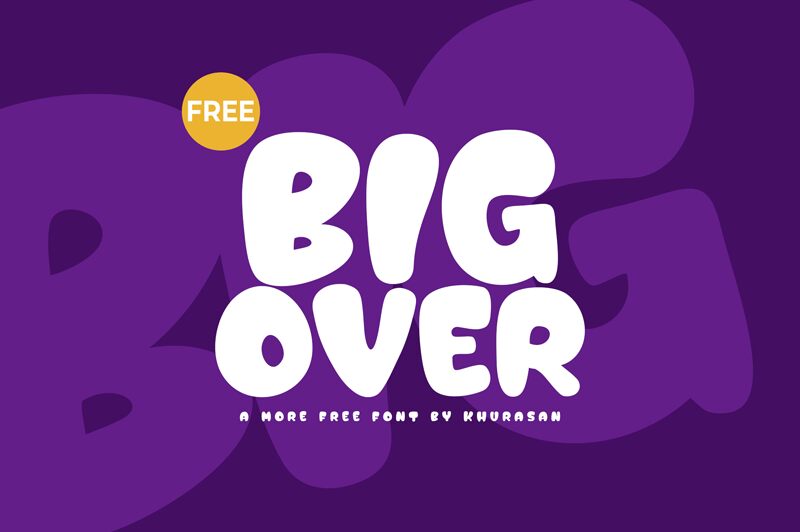
Bigover od Khurasan je bezplatné kreslené titulkové písmo postavené na masivních, lehce nepravidelných verzálkách s hravým, ručně kresleným dojmem. Vypouklé křivky, nerovnoměrné proporce a malé uzavřené prostory dodávají písmenům energii animovaných titulků, aniž by potřebovaly další ozdoby.
Toto bezplatné písmo se skvěle hodí na obálky dětských knih, obaly snacků, komiksové nadpisy, herní loga, plakáty na akce i hravý merchandising. Jeho výrazné tvary a živý rytmus fungují obzvláště dobře u krátkých titulků, kde několik velkých slov dokáže utáhnout celou kompozici.